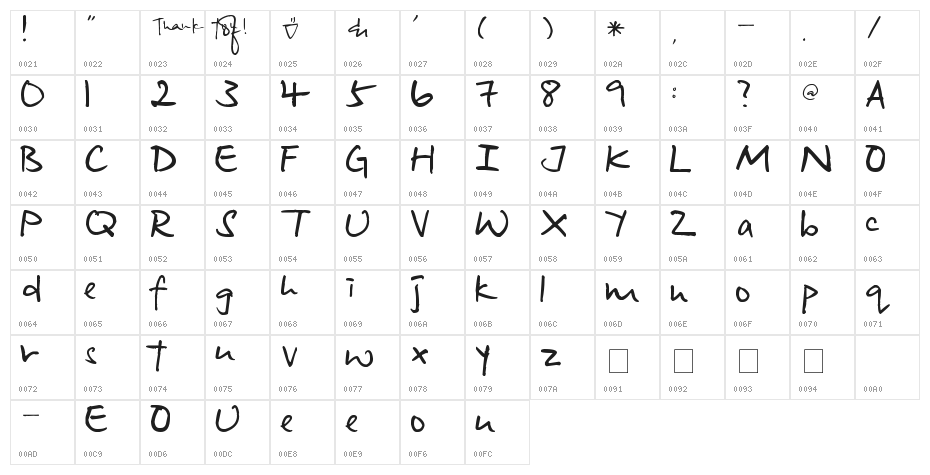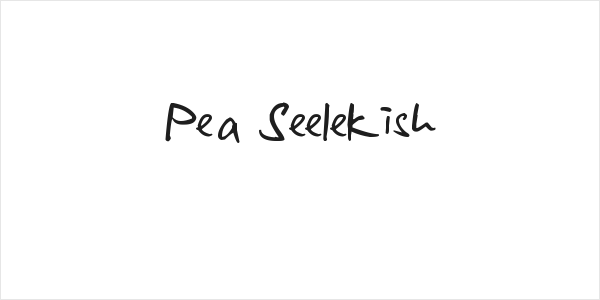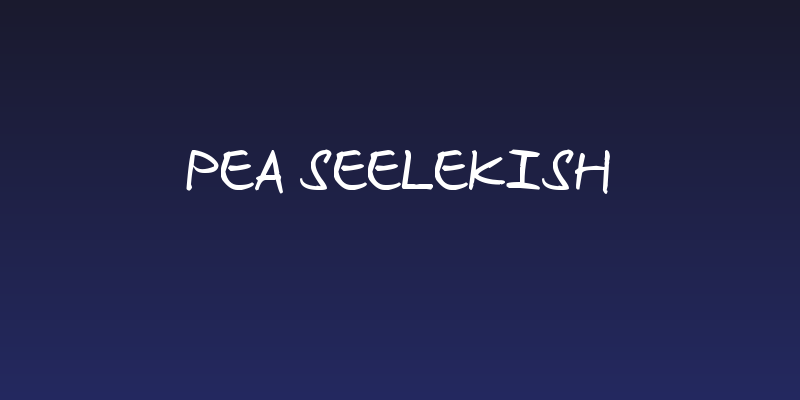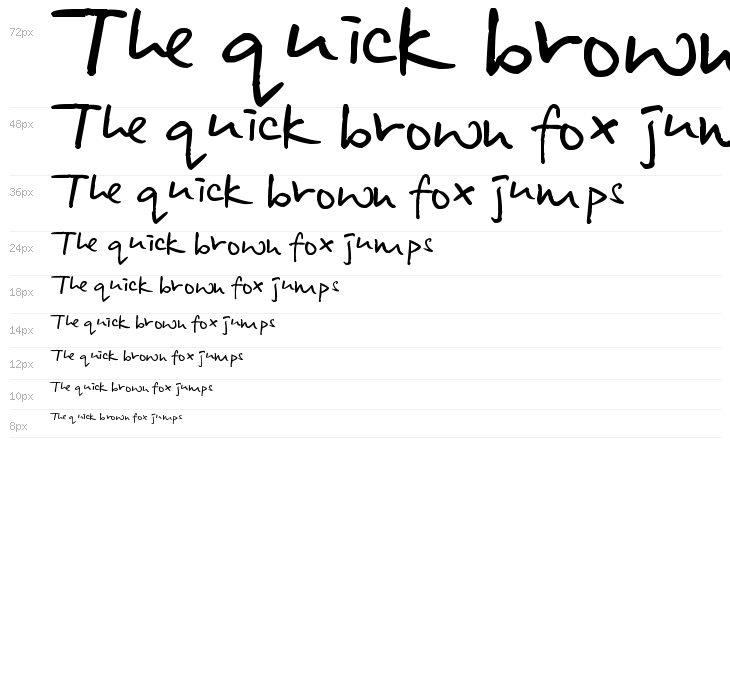
Pea Seelekish Font
✎ Handwritten
| 整体风格 | Casual, Playful |
| 使用场景 | Headlines, Informal text, Creative projects |
| 推荐项目 | Ideal for greeting cards, personal blogs, informal invitations, and creative projects requiring a personal touch. |